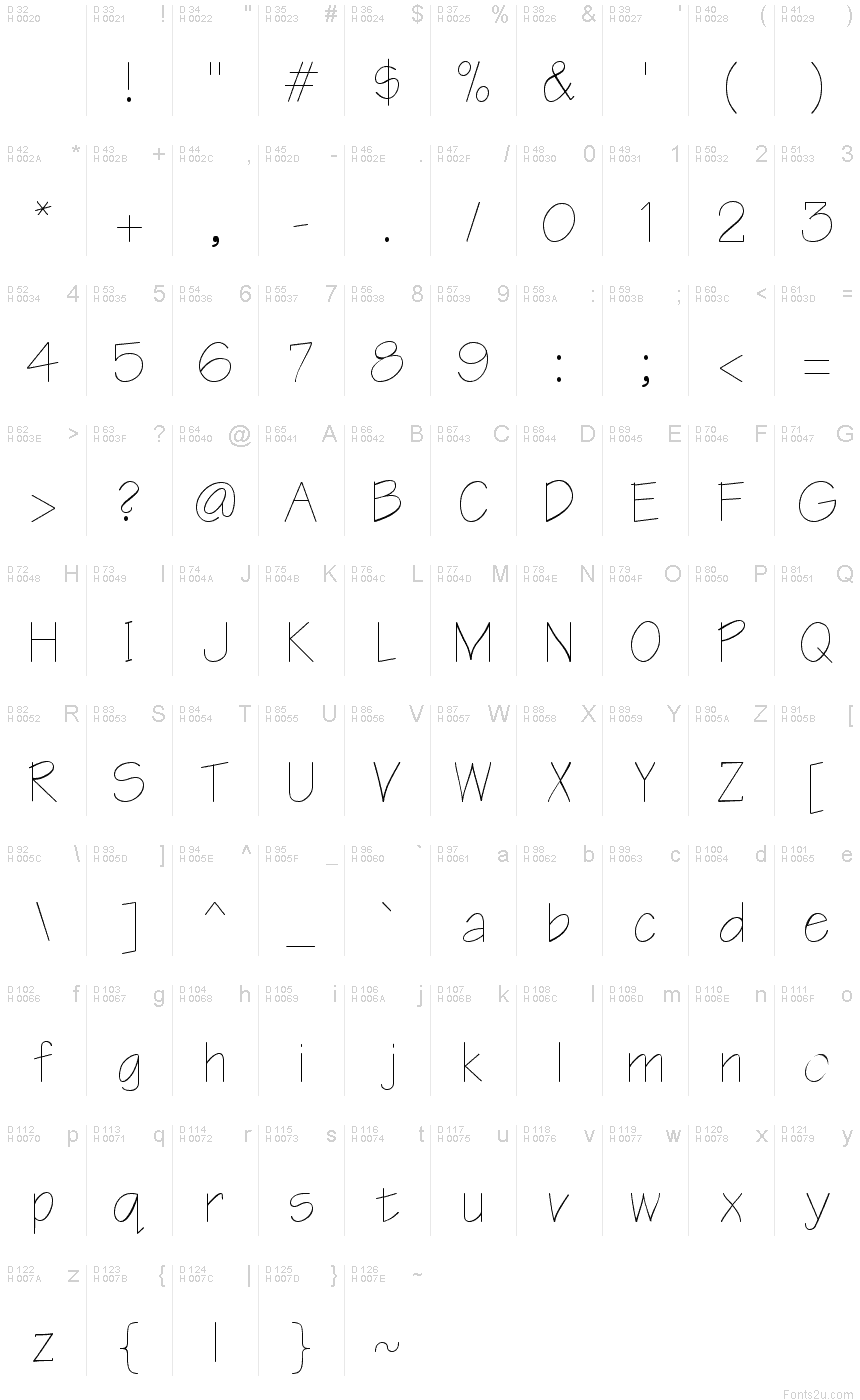
معاينة خط ER Architect 866
خط ER Architect 866 من تصميم Gavin Helf هو خط مجاني مكتوب بخط اليد يجسد المظهر النظيف والدقيق لمفكرة المهندس المعماري دون التضحية بوضوح القراءة. بفضل حروفه الطويلة والضيقة، ومسافاته المتوازنة، وخطوطه ذات السماكة الموحدة، يبدو الخط وكأنه ملاحظات مدونة بعناية بقلم تقني، مما يمنحه طابعاً غير رسمي ولكنه منظم بعيداً عن الفوضى. استخدمه عندما ترغب في الحصول على خط يد يبدو شخصياً ومنظماً في آن واحد، خاصة في الأماكن التي قد تبدو فيها الخطوط الثقيلة والمتكدسة مزدحمة.
مع ER Architect 866، يمكنك إضافة طابع هادئ وفكري إلى لوحات الإلهام (Moodboards)، والمخططات، والنماذج الأولية (Wireframes)، وتوضيحات الواجهات، والمواد التعليمية، وتسميات الأعمال الفنية، والملصقات ذات الطابع الاسكتشي. يتألق هذا الخط المجاني عند استخدامه بأحجام متوسطة، حيث تظل خطوطه الرفيعة واضحة وخفيفة. يمكنك تنسيقه مع خط Sans Serif هندسي بسيط للعناوين للحفاظ على هيكلية التصميم، بينما يتولى ER Architect 866 إضافة اللمسة الإنسانية التي يضفيها الخط اليدوي.